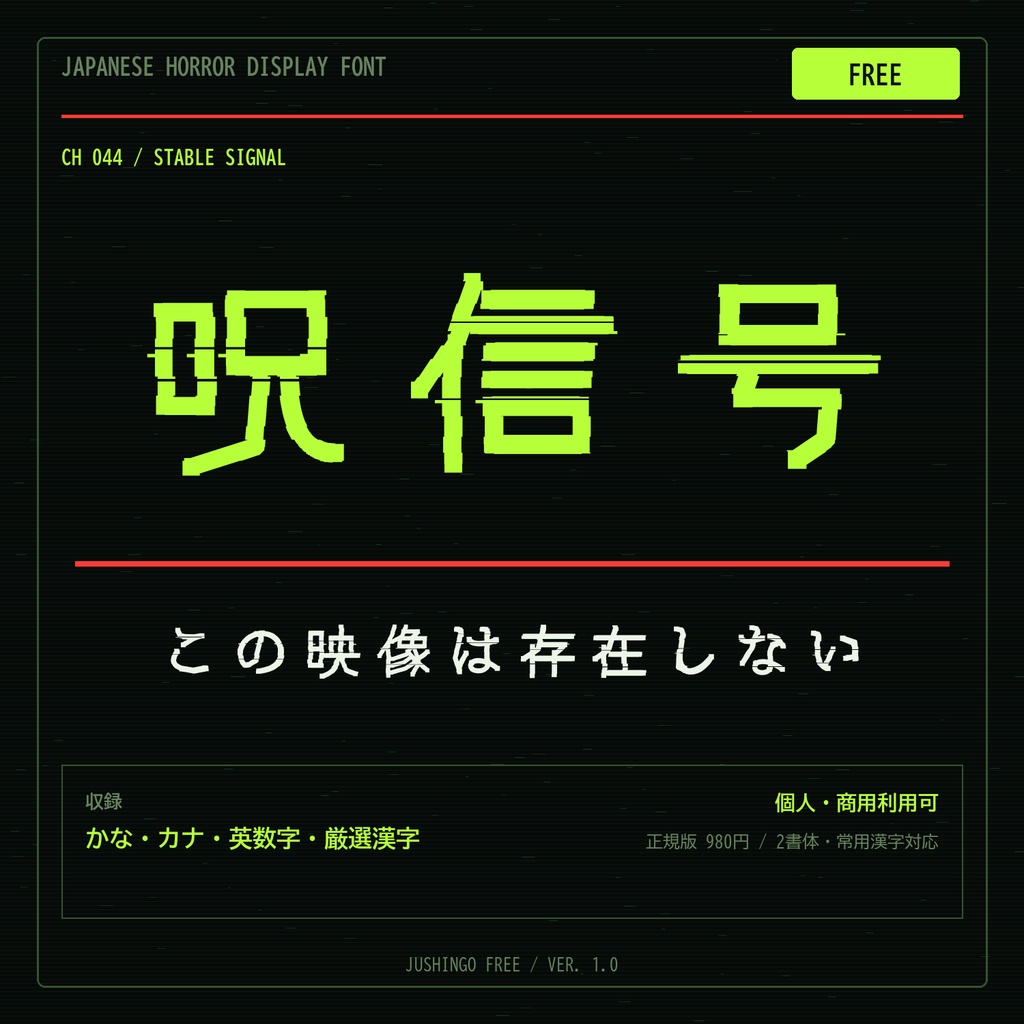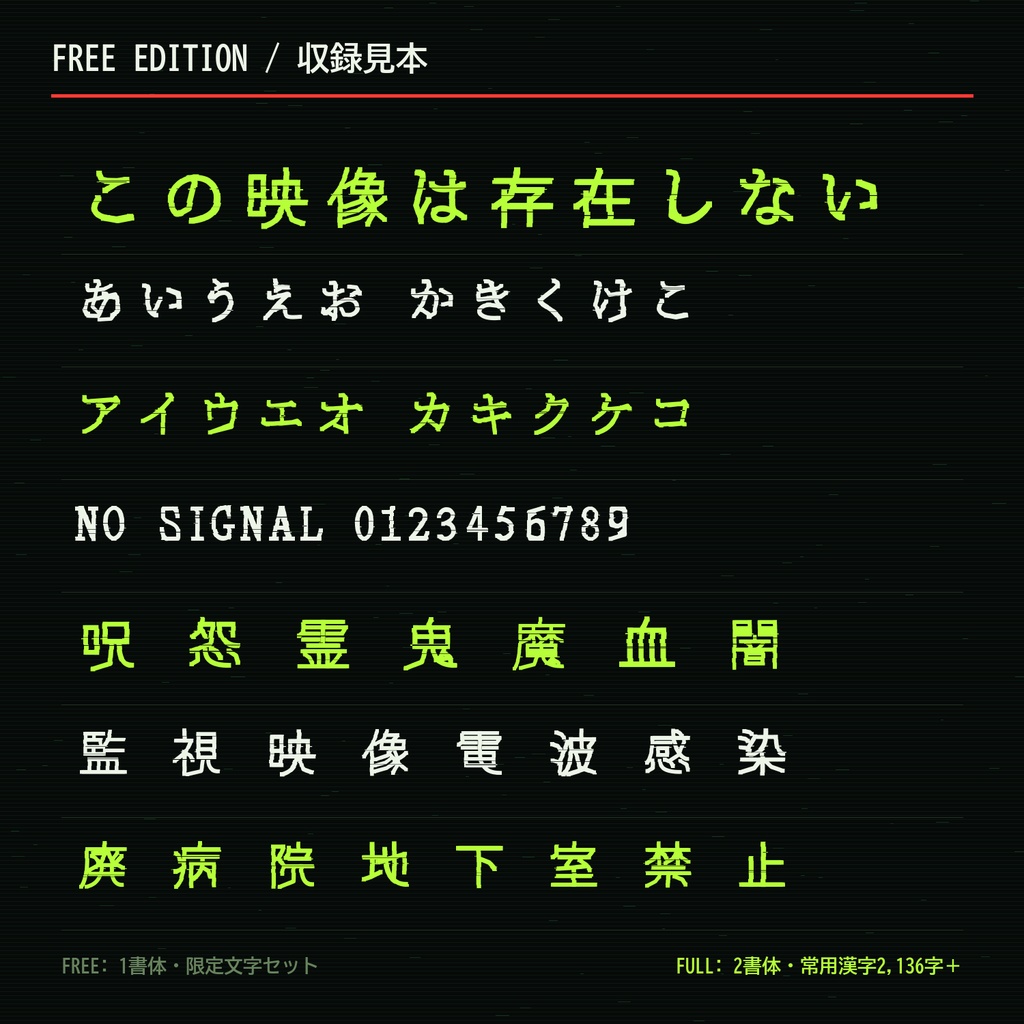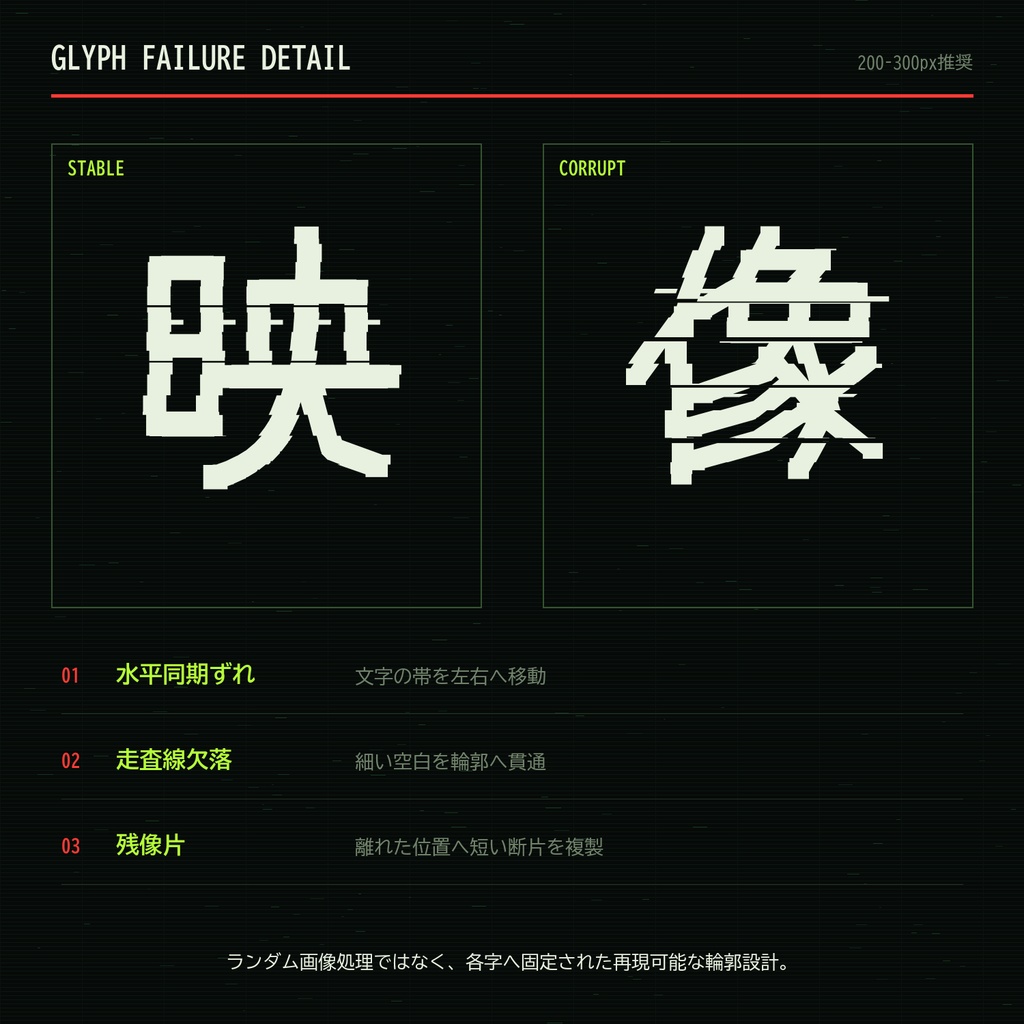
【無料版】呪信号|VHS・監視映像ホラー向け日本語フォント
【無料版】呪信号 / JUSHINGO FREE 読める。けれど、映像のどこかが壊れている。 横方向の同期ずれ・走査線欠落・残像片を字形へ組み込んだ、VHS・監視映像ホラー向け日本語フォントです。 ■ 無料版の内容 ・JushinGo Free 1書体(Stableを基にした可読性優先版) ・ひらがな、カタカナ、英数字、基本記号 ・呪、霊、怨、鬼、魔、監視、映像、電波、感染、廃、病院など厳選漢字を収録 ・個人・商用利用可、クレジット不要 ■ 向いている用途 アナログホラー、TRPG、マーダーミステリー、動画テロップ、配信サムネイル、ゲーム画面、同人誌。 ■ 正規版との違い 正規版(980円)はStable/Corruptの2書体を収録し、ひらがな・カタカナ・英数字・常用漢字2,136字+ホラー用字を使用できます。 ■ 形式 TrueType(TTF)/ Windows・macOS ※フォントファイルそのものの再配布・共有・転売は禁止です。 ※詳細はZIP内の利用規約をご確認ください。